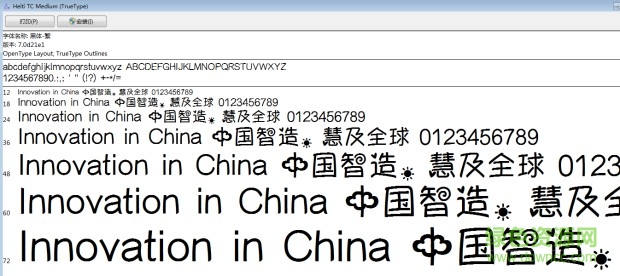
云彩圈圈字體
蝴蝶結(jié)云彩圈圈字體是一款非常逗趣可愛的萌字體哦,這類字體擁有各種小可愛的形狀,還有超多不一樣的字形,有喜歡的就來綠色資源網(wǎng)下載吧!
蝴蝶云彩圈圈字體介紹
蝴蝶結(jié)云彩圈圈體是一款非常受歡迎的簡體字體,這款字體不僅有著非常和諧美觀的字體結(jié)構(gòu),而且筆畫設(shè)計(jì)新穎,流暢可愛,辨識(shí)度很高,一經(jīng)推出便受到了廣大學(xué)生們和美術(shù)設(shè)計(jì)師門的喜愛,可作為廣告字體和日記字體使用。
蝴蝶云彩圈圈字體預(yù)覽